今回は、小宮山博史著の『明朝体活字 その起源と形成』を紹介します。
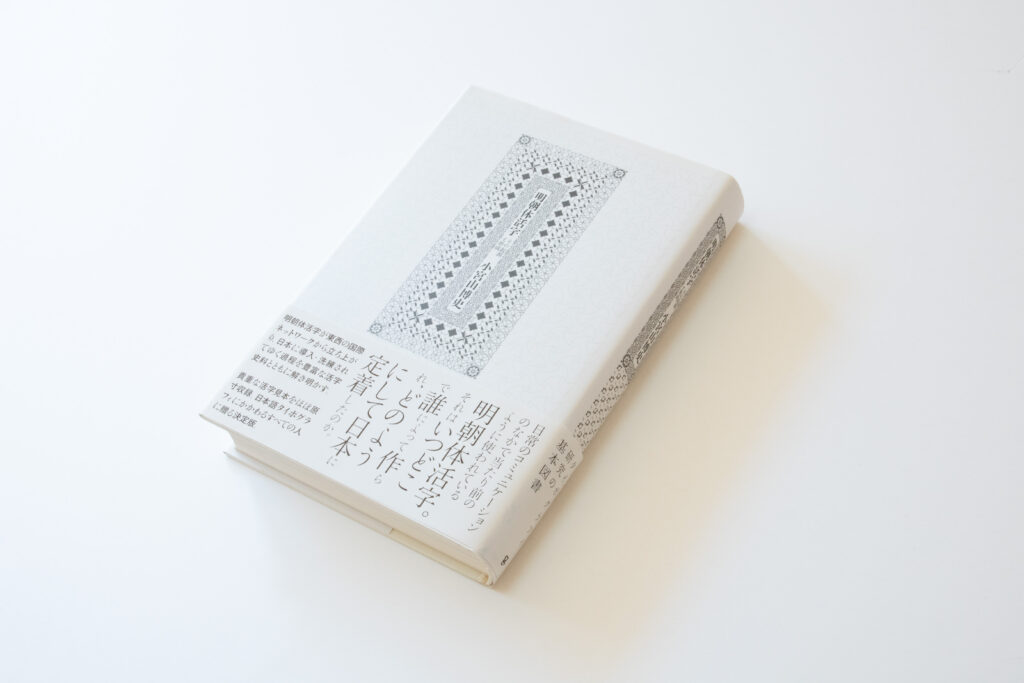
ずっしりと大きめの本で内容もぎっしりと詰まっているのですが、小宮山先生の柔らかな文体と、文章と関連図版を一緒に追えるよう設計された丁寧な紙面で、読み口は優しく感じます。
本書は「もしかすると金属活字の明朝体は中国人ではなくヨーロッパ人が作ったのか?」という疑問から始まりました。そして実際にアジアの国々に留まらず、フランス、イギリス、オーストリアなどヨーロッパの国々も明朝体の形成に関わったことが示されています。さらにそれがいかにして日本に伝わり、国内でどんな発達を経て現代に至るのか。広く長い明朝体の歴史を解き明かそうとする内容です。
豊富な資料がほぼ原寸大で収録されていること、都度細かく活字サイズが確認されていること、そして第八章本文の文字サイズにも注目したいです。金属あるいは木や粘土の活字は大きさが固定されています。大きさが明確であることはより極まったデザインを可能にします。この本が体験させてくれるリアルな大きさから、これは当時の文字がくっきりとした美しさをもつ要因の一つなのだと実感させられました。
『明朝体活字 その起源と形成』